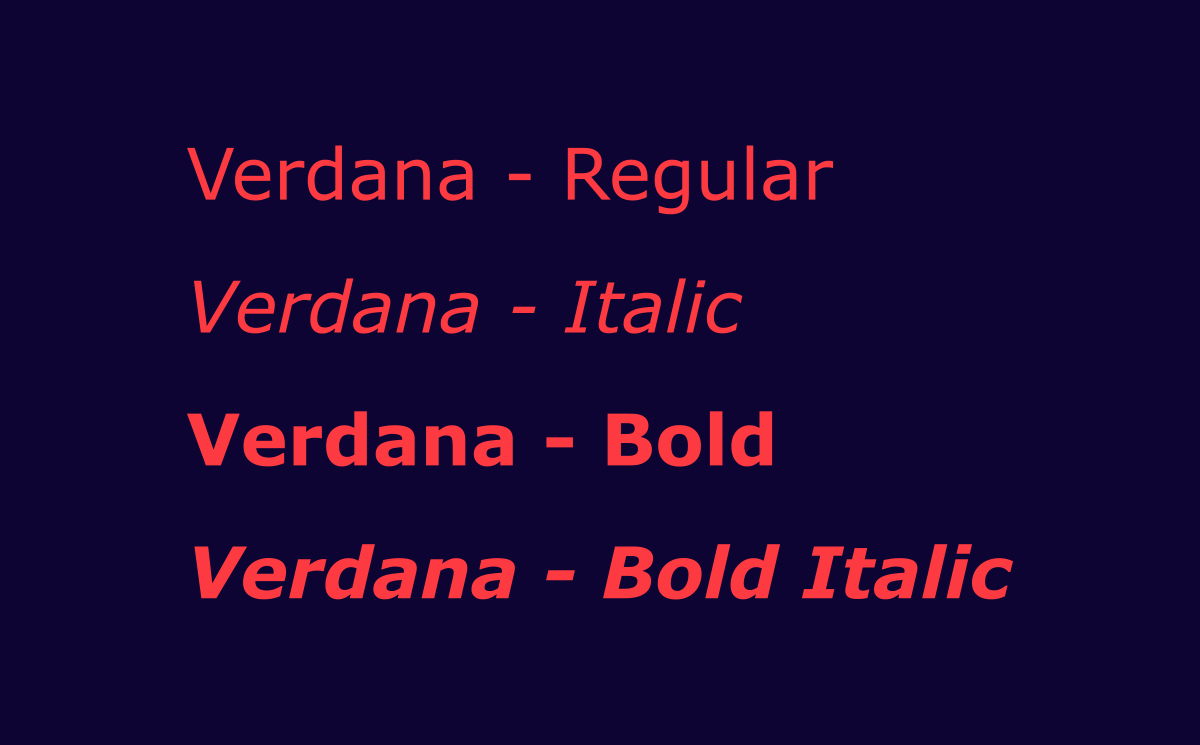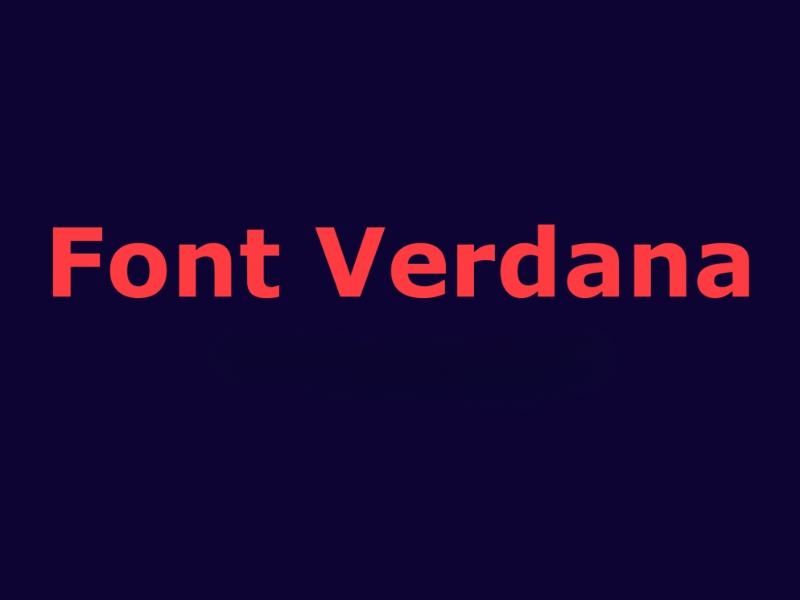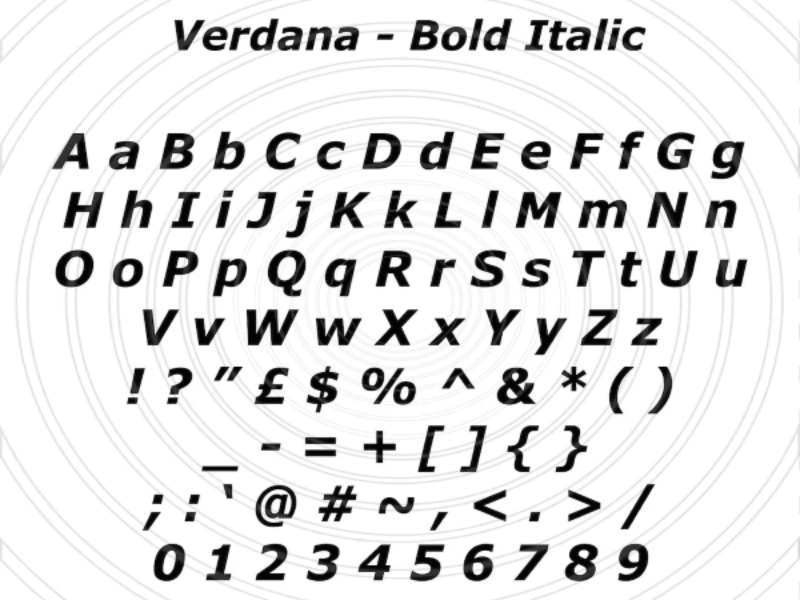
Bạn đang tìm bộ font Verdana Việt hóa chất lượng để thiết kế và in ấn, nhưng nhiều phiên bản trên mạng thường thiếu dấu tiếng Việt hoặc định dạng hạn chế, gây khó khăn khi sử dụng. Bài viết này, Inviva sẽ cung cấp 15+ mẫu font Verdana Việt hóa, giúp bạn dễ dàng tải về, chỉnh sửa và áp dụng cho mọi dự án thiết kế chuyên nghiệp.
Font chữ Verdana Việt hóa có nhiều phiên bản phù hợp với từng mục đích sử dụng khác nhau, từ văn bản dài, báo cáo, đến tiêu đề và ấn phẩm quảng cáo. Việc hiểu rõ các phiên bản này sẽ giúp bạn chọn đúng kiểu chữ, đảm bảo tính thẩm mỹ và đồng bộ trong mọi thiết kế.
Dưới đây là bảng tổng hợp các phiên bản font Verdana Việt hóa được trình bày rõ ràng, gọn gàng và dễ tham khảo, phù hợp với kiểu bài chuyên nghiệp:
Phiên bản font |
Đặc điểm | Ứng dụng |
Verdana Regular Việt hóa |
Nét chữ đều, chuẩn mực | Văn bản, tài liệu, báo cáo, nội dung dài |
Verdana Bold Việt hóa |
Nét đậm, nổi bật |
Tiêu đề, banner, ấn phẩm quảng cáo |
| Verdana Italic Việt hóa | Nghiêng, mềm mại |
Chú thích, trích dẫn, tagline thương hiệu |
| Verdana Bold Italic Việt hóa | Kết hợp đậm và nghiêng |
Tiêu đề nổi bật, poster sự kiện, banner quảng bá |
Giới thiệu phông chữ Verdana
Verdana là phông chữ sans-serif Humanist do Matthew Carter thiết kế cho Microsoft năm 1993, tối ưu hóa khả năng đọc trên màn hình độ phân giải thấp. Với cấu trúc chữ rộng, khoảng cách ký tự lớn và x-height cao, Verdana rất dễ đọc ngay cả ở kích thước nhỏ, phù hợp cho web, email và giao diện người dùng.
Tên gọi “Verdana” kết hợp giữa “verdant” (xanh lá) và “Ana” – con gái của Virginia Howlett, người khởi xướng dự án. Thiết kế của Verdana giúp văn bản rõ ràng, dễ đọc, với nét chữ đậm giữ độ nét tốt trên mọi màn hình.
Verdana được sử dụng phổ biến trên web, ứng dụng, email marketing và các văn bản dài nhờ tính dễ đọc cao. So với Tahoma, Verdana rộng hơn và thích hợp cho nội dung văn bản, trong khi Tahoma thường dùng cho nhãn hoặc menu.
Ý nghĩa và ứng dụng font chữ Verdana Việt hóa
Phông chữ chữ Verdana Việt hóa là lựa chọn phổ biến nhờ tính dễ đọc, hiện đại và linh hoạt trong nhiều dự án thiết kế. Sử dụng font này giúp đảm bảo đồng bộ thương hiệu, tăng tính chuyên nghiệp và truyền tải thông điệp rõ ràng trên cả màn hình kỹ thuật số lẫn ấn phẩm in.
- Đường nét rõ ràng, chuẩn mực, dễ đọc trên mọi kích thước và nền.
- Hỗ trợ đầy đủ ký tự tiếng Việt có dấu, hạn chế lỗi hiển thị khi thiết kế hoặc in ấn.
- Thích hợp cho văn bản, báo cáo, website, banner, tiêu đề và các ấn phẩm marketing.
- Tăng tính chuyên nghiệp và đồng bộ cho thương hiệu trong mọi ứng dụng.
5 sai lầm khi sử dụng font Verdana Việt hóa
Khi dùng font Verdana Việt hóa, nhiều người thường mắc phải một số lỗi phổ biến ảnh hưởng đến thẩm mỹ và hiệu quả truyền tải thông điệp:
- Sử dụng font không đầy đủ ký tự tiếng Việt: Một số phiên bản font không hỗ trợ toàn bộ dấu tiếng Việt, dẫn đến lỗi hiển thị, thiếu dấu hoặc sai ký tự khi in ấn.
- Lạm dụng nhiều kiểu chữ cùng lúc: Kết hợp quá nhiều phiên bản (Regular, Bold, Italic, Bold Italic) trong cùng một thiết kế làm mất sự đồng bộ, rối mắt và giảm tính chuyên nghiệp.
- Dùng file raster thay vì vector: Sử dụng ảnh PNG/JPG thay vì cài đặt font TTF/OTF gốc sẽ khiến chữ bị mờ, răng cưa khi in khổ lớn hoặc phóng to.
- Thiếu kiểm tra khi in ấn: Không chuyển text thành outline hoặc kiểm tra trước khi in có thể dẫn đến sai lệch font, màu sắc và kích thước trên sản phẩm cuối cùng.
Áp dụng đúng cách Font Verdana sẽ giúp thiết kế vừa rõ ràng, vừa chuyên nghiệp, đồng thời đảm bảo nhận diện thương hiệu hiệu quả.
Bổ sung đầy đủ ký tự tiếng Việt có dấu, giữ nguyên nét chữ chuẩn, dễ đọc, phù hợp thị trường Việt Nam.